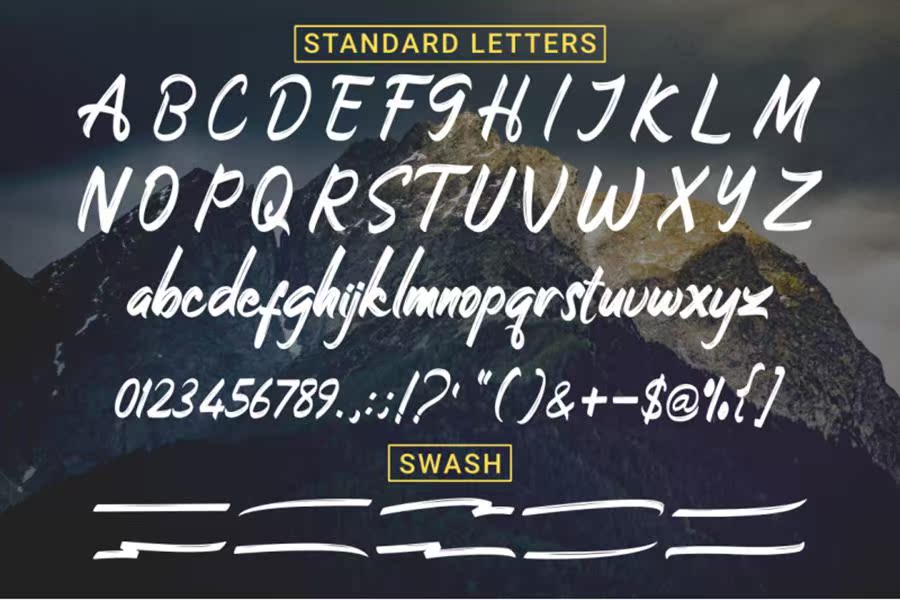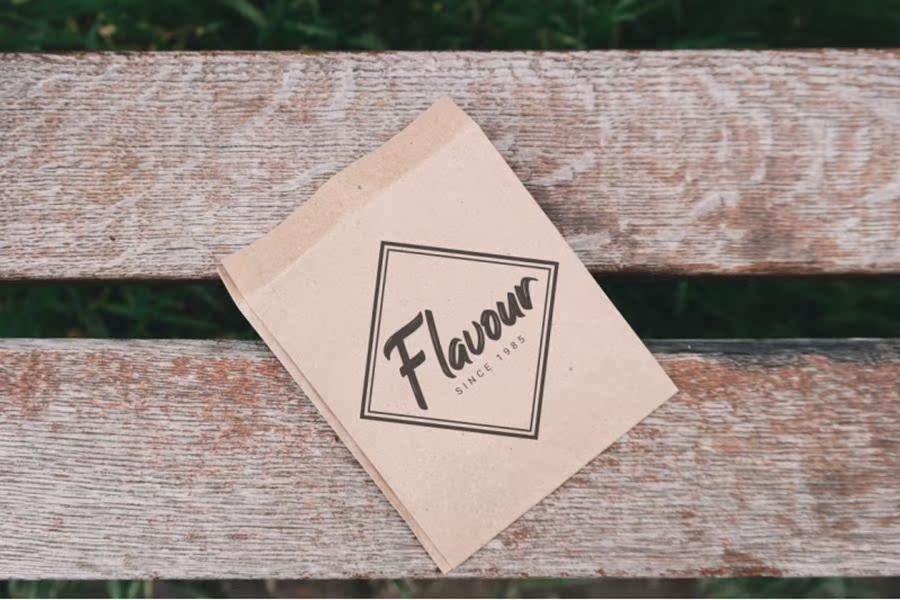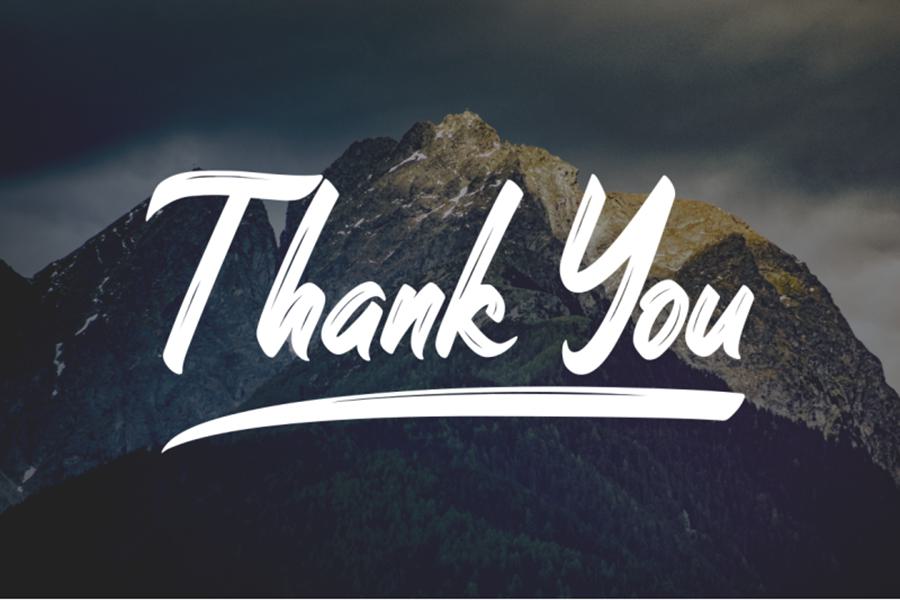
StoneHoleScriptfreedemois具有纹理和永恒的手写字体。使用粗体笔划和擦洗,它可以轻松地将任何设计项目旋转和拉出!此FontIsabrushScriptFontWithReal Hand Brushed Characters。此FontIsabrushScriptFontWithReal Hand Brushed可折叠,但可通过文本格式转换为MakeSitSitedEntity。您可以看到,此FontIsabrushScriptFontWithBranding可用于品牌、徽标。